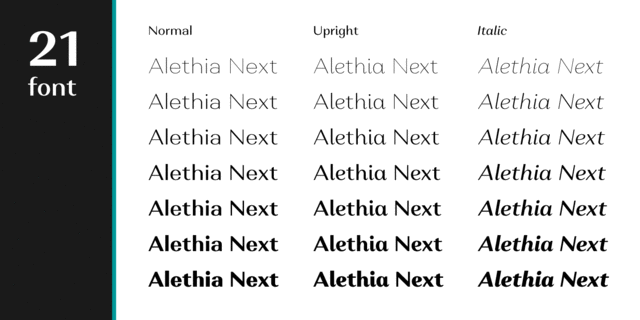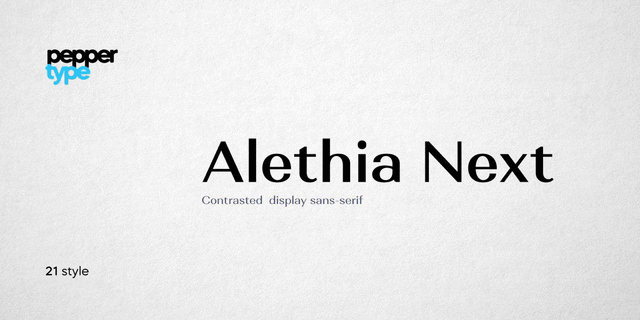
Alethia Next – это шрифт без засечек с высокой контрастностью во всех насыщенностях. Он предназначен для акцидентного использования в различных редакционных проектах, таких как журналы и корпоративные брошюры, в качестве гротесковой пары к современным антиквам. Семейство имеет 7 весов жирности + курсивы + прямые курсивы. Каждое начертание поддерживает множество языков на кириллице и латинице, включая болгарские грефемы. Гарнитура содержит OpenType фичи, такие как лигатуры, капитель и многочисленные альтернативные глифы. Alethia Next разработал Олег Лищук в 2019 году.
тонкий, худой, утонченный, холодный, деликатный, чистый, легкий, прохладный, свежий, модный, качественный, культурный, отборный, благородный, гармоничный, элитный, дорогой, роскошный, красивый, мастерский, знаменитый, оригинальный, богатый, современный, городской, прозрачный, проволочный, точный, гладкий, твердый, четкий, резкий, прямой, статичный